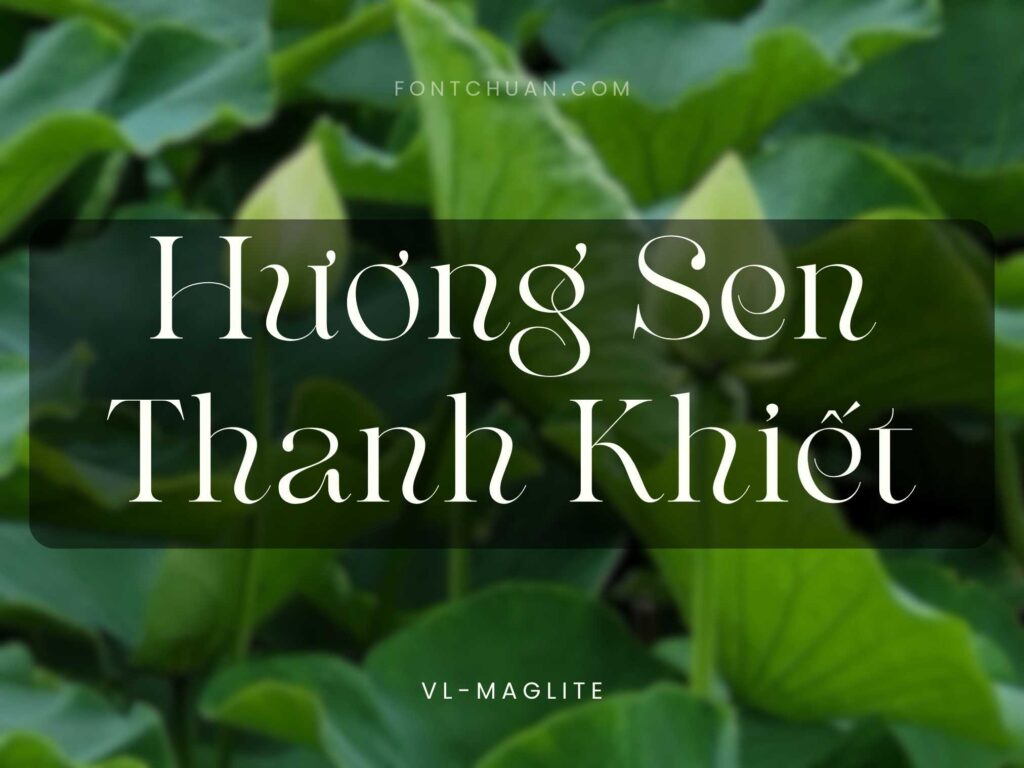
Font VL Maglite Việt Hóa
VL-Maglite là một phông chữ serif hiện đại và tinh tế, được thiết kế bởi Sarid Ezra. Phông chữ này nổi bật với các chữ ghép đẹp mắt và các chữ xen kẽ uốn lượn, tạo nên sự độc đáo và thu hút cho các thiết kế. VL-Maglite đã được Việt hóa bởi Việt Linh, hỗ trợ đầy đủ các ký tự tiếng Việt, giúp người dùng dễ dàng áp dụng trong các dự án sáng tạo. Phông chữ này được thành viên Font Chuẩn sưu tầm và đăng tải nhằm phục vụ nhu cầu thiết kế đa dạng.
Với thiết kế thanh lịch và mềm mại, VL-Maglite phù hợp cho các ứng dụng như thiệp cưới, bao bì sản phẩm, bìa sách, typography và trích dẫn. Trong lĩnh vực sự kiện, phông chữ này có thể được sử dụng trong các dịp như lễ hội, thiệp cưới và sinh nhật. Ngoài ra, VL-Maglite cũng thích hợp cho các ngành nghề như quảng cáo, giáo dục và công nghệ.